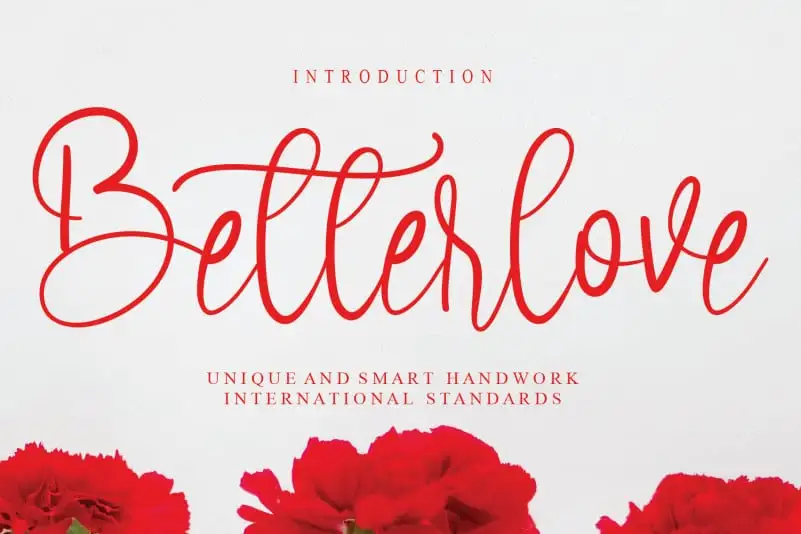
Betterlove Calligraphy Font – Fonte Grátis
Betterlove Calligraphy Font
Descubra a magia do ‘Betterlove Calligraphy Font’, uma elegante escolha para quem valoriza a delicadeza e sutileza nos design gráfico. Desenvolvida pelo designer creativeletter, essa fonte script é perfeita para criadores que buscam um toque de profissionalismo em suas criações enquanto mantêm um estilo único e autêntico. Com seus traços fluidos e delicados, você pode explorar uma variedade de estilos desde elegantes cartões de aniversário até registros poéticos. É perfeita para aqueles que valorizam a forma e o conteúdo em igual medida, oferecendo tanto personalidade quanto sofisticação. Com sua versão ‘Betterlove Calligraphy Font’, explore as possibilidades criativas do design digital, seja você um profissional ou um amante da arte.